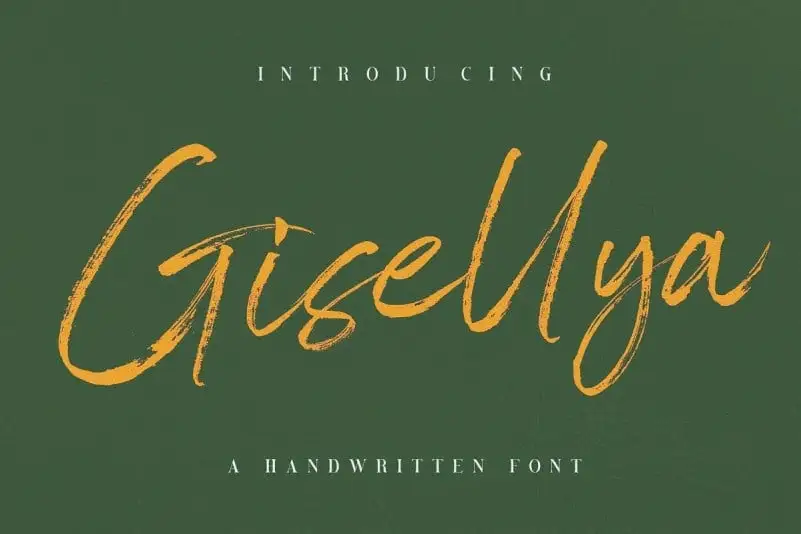
A Gisellya Brush Font é uma elegante mistura de letra cursiva moderna e autêntica mão-digital que transmite um ar refinado e sofisticado. Inspirada no estilo manuscrito, essa fonte tem uma sensação delicada e sofisticada, parecendo perfeitamente adaptada para qualquer projeto que busque um toque elegante e atual. Ideal tanto para nomes de empresas quanto para criações gráficas pessoais ou projetos publicitários, a Gisellya Brush Font se destaca por sua natureza fluente e fluida, dando ao texto uma aparência encantadora e moderna. Como design do designer 99designs, essa fonte é um marco no campo das letras manuscritas digitais, oferecendo aos criadores de conteúdo o poderoso instrumento para incorporar um toque personalizado à sua próxima criação gráfica.